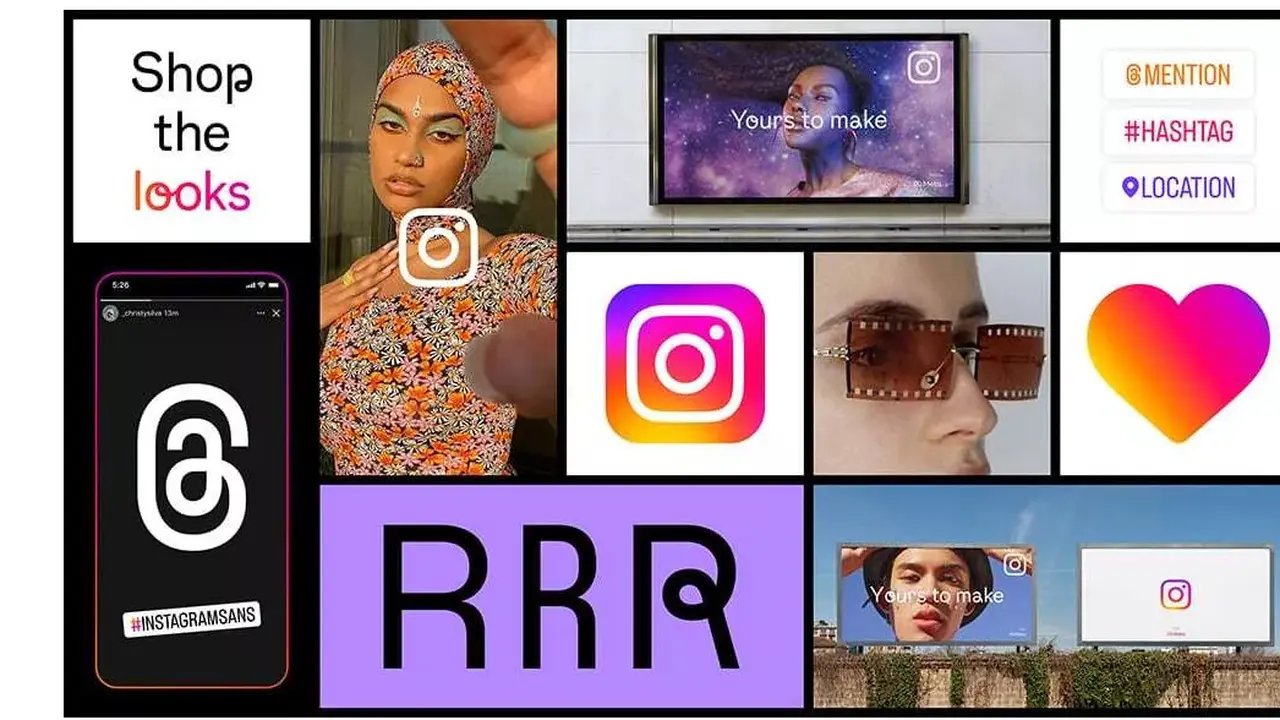
Liputan6.com, Jakarta - Instagram menggulirkan tampilan identitas baru yang lebih segar untuk dipakai pengguna dan influencer. Kehadiran tampilan identitas baru ini merupakan bentuk penyegaran visual yang diharapkan bakal menumbuhkan kreativitas di berbagai komunitas.
Ada tiga bagian dari penyegaran ini, yakni font baru bernama Instagram Sans, tata letak dan sistem desain baru, serta logo dengan gradien warna baru.
Mengutip Tech Radar, Selasa (24/5/2022), Instagram Sans merupakan font global baru Instagram yang terinspirasi dari logo Instagram. Perusahaan mengatakan, pihaknya bekerja sama dengan para ahli untuk memastikan bahwa font ini bisa dipakai di berbagai bahasa, termasuk bahasa Jepang dan Arab.
Instagram Sans menampilkan motif melingkar yang fleksibel. Pengguna disebut-sebut bisa menggunakan Instagram Sans di situs website About Instagram. Pengguna juga bisa mengecek sub-font baru seperti Sans Script dan Medium.
Selain itu, untuk layout baru Instagram dimaksudkan untuk mendobrak batas desain Instagram saat ini dan menciptakan kolase tanpa batas, dalam portrait maupun lanskap.
Ada opsi empat layout Instagram, yakni 1:1, 4:5, 9:16, dan 16:9. Pengguna bisa memakainya tidak hanya pada gambar tetapi juga di Reels maupun Stories. Kreator juga bisa menambahkan link produk ke layout baru Instagram.
Sementara untuk tampilan baru Instagram untuk gradien warna pada logo, hanyalah bentuk logo yang bisa ditemukan di berbagai bagian Instagram, mulai di Create, cincin di sekitaran Instagram Stories, dan stiker di Instagram Stories.